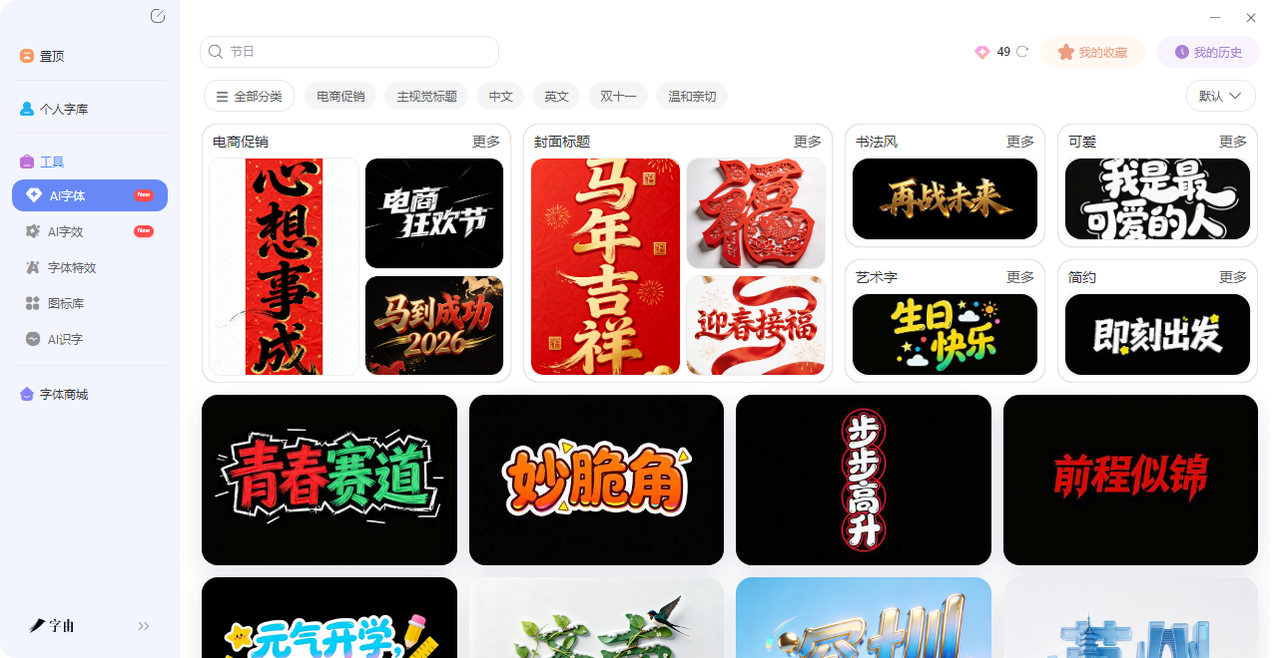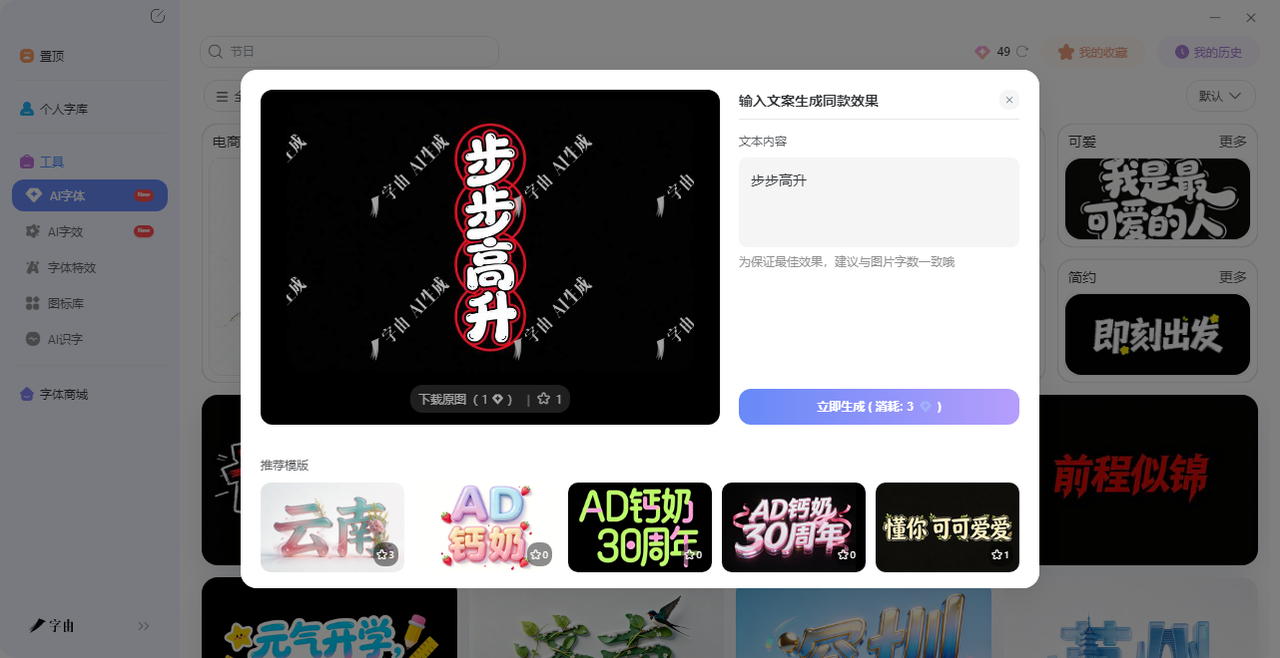
不会设计字体?这几个字体生成器一键搞定
每次刷到别人设计的海报,最让我眼馋的不是构图多精妙,而是那几个标题字——金属质感、霓虹闪烁、水彩晕染,怎么看怎么高级。自己也想要同样的效果。但是在发现捷径之前,我都是自己一板一眼地设计,但是困难重重并且效率非常低。后来我发现,这种“想要又做不出来”的尴尬,根本不是技术问题,而是没用对工具。今天要聊的字体生成器,就是专门解决这个问题的,今天介绍的这5个字体生成器绝对能帮到你,需要的快收藏吧!
字由的“AI字体”功能,本质上就是一个字体生成器。它把霓虹、金属、国潮、手写这些效果做成了模板,你只需要输入文字,选个顺眼的,点一下生成,就能拿到一张带特效的艺术字。不需要下载字体,不需要安装软件,甚至不需要打开PS——整个过程都在浏览器里完成,最后下载透明背景PNG,拖进设计软件就能用。
具体怎么使用呢,下面是简要的步骤:
- 第一步:在导航栏找到【字体工具】→【AI工具】→【AI字体】。
- 第二步:进入页面后,搜索框里输入你想要的效果,系统会筛出对应的模板。鼠标滑过模板,就能看到用你的文字实时展示的效果。这些模板不是那种千篇一律的预制货,而是真的考虑了不同设计场景。比如做电商促销,有“限时特惠”“满300减50”这种冲击力强的;做节日海报,有“元宵节快乐”“生日快乐”这种氛围感足的;做品牌Logo,有“CLASSY”这种高级简约的。每个模板点进去还能微调,颜色、背景、字间距都能改,不是那种“生成出来就定型”的死板工具。所以哪怕同一个模板,你改个颜色、换种排版,也能做出不一样的感觉。
- 第三步:选一个喜欢的,点击“做同款”,把模板里的文字换成你的标题(最好字数一致)。
- 第四步:点“立即生成”。等20-30秒,就能拿到一张高清艺术字图片。下载时可以选择透明背景,直接用在设计里。
步骤十分简单,哪怕你是0 基础的新手,也能够完全使用。而且字由的AI字体模板库非常丰富,按场景分好了类:电商促销、主视觉标题、节日、国潮、科技、手写……每个分类下都有几十种风格。如果你有自己常用的字体,也可以先用字由的字体库选好基础字体,再用“AI字效”功能给它加特效,同样是一键搞定。
生成的图片可以直接用在海报、封面、短视频里。透明背景的PNG拖进PS、Canva、剪映,不需要抠图,不需要调色,直接叠加就行。如果你用的是PS、AI、Figma这些软件,字由的客户端还能一键应用字体——选中文字图层,在字由点一下,文字实时切换,不用下载安装。
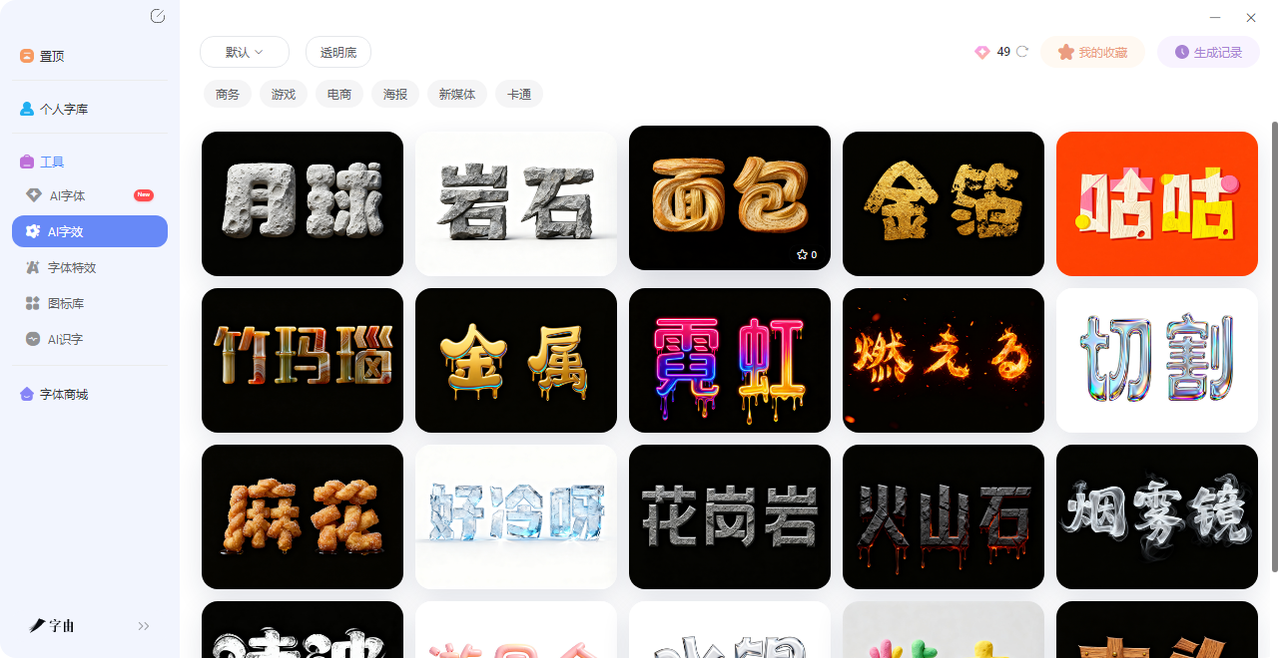
2、Font Generator
这个字体生成器和字由不一样,它不生成图片,而是把普通文字转换成各种花式字体,然后让你直接复制粘贴。适合用在社交媒体个人简介、评论区、游戏昵称等地方。打开网页,在输入框里打字,下面会立刻列出几十种不同风格的字体:粗体、斜体、手写体、哥特体、气泡体、上下颠倒体……点一下旁边的“Copy”按钮,就能复制到剪贴板,直接去微信、微博、抖音里粘贴。完全免费,无需注册。
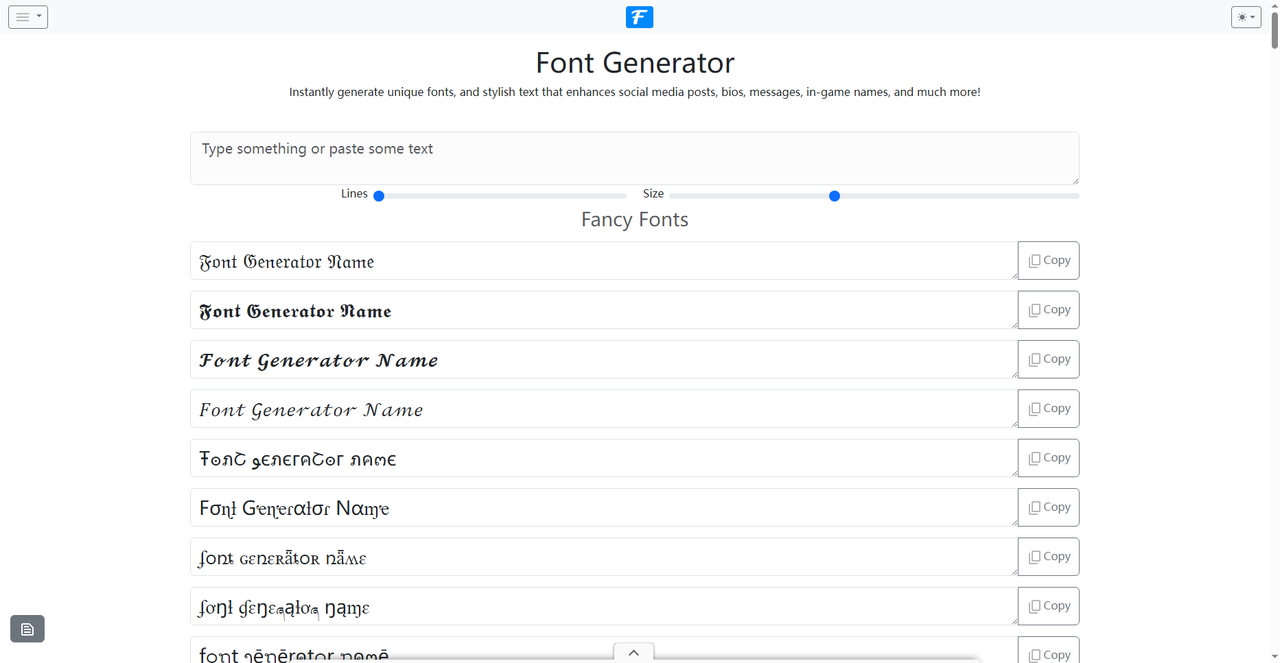
3、Fancy Text Generator
这个工具和上面那个类似,也是把普通文字转换成Unicode花式字体。但它的分类更细:下划线字体、草书字体、删除线字体、哥特字体、粗体、小字体、故障字体、气泡字体、上下颠倒字体、美学字体……总共加起来几十种。操作一样简单:输入文字,下方自动生成各种样式,点复制就行。适合喜欢在社交平台上“整活”的用户,发个带特殊字体的文案,回头率很高。
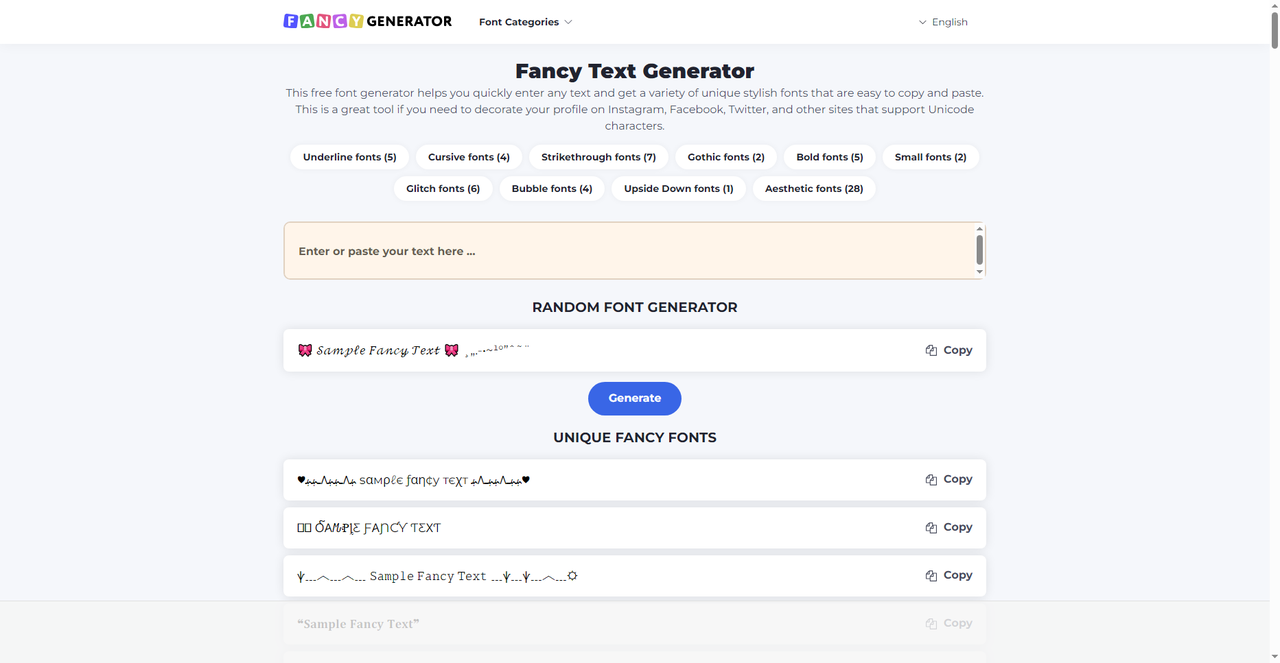
4、Fancy Text Generator
这个工具也是做文字转换的,但它多了一个功能:生成随机花式字体。点击“Generate”按钮,系统会随机给你几个不同风格的字体方案。适合懒得翻列表、只想碰运气的用户。它还附带了一个解释,告诉用户这些花式字体的原理——不是真的改变了字体,而是用了Unicode里的特殊字符。虽然技术原理讲得清楚,但普通用户只需要知道“怎么用”就够了。
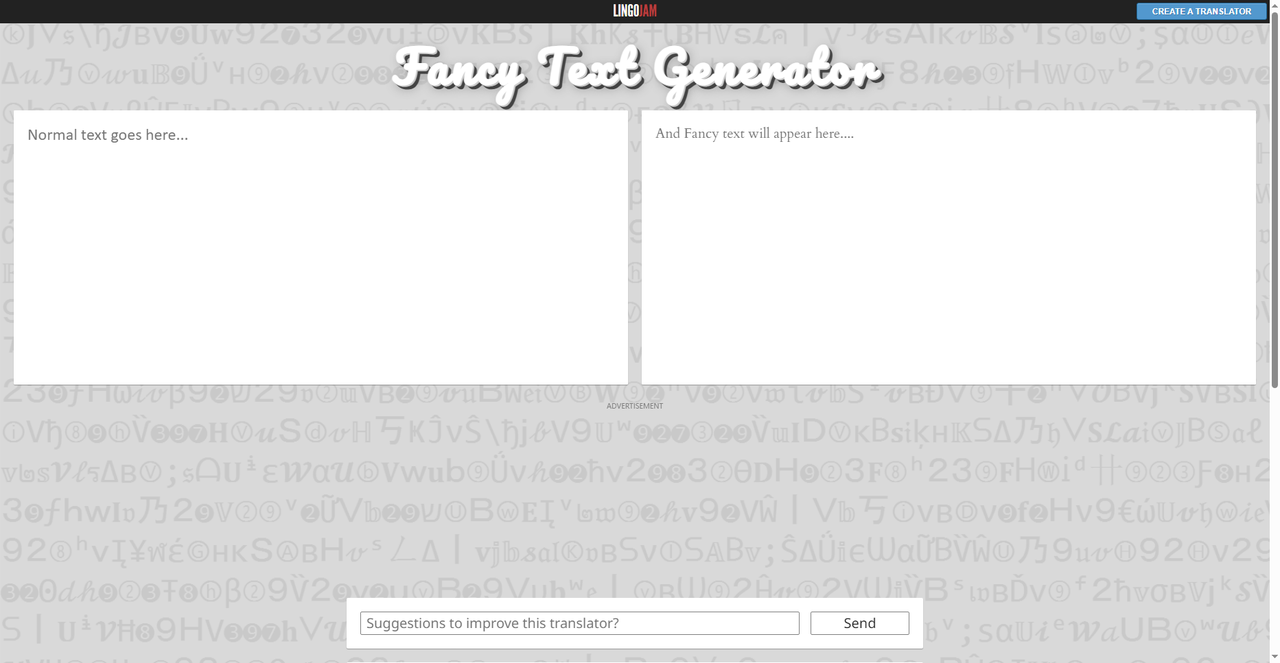
5、Musely
最后这个是一个中文的AI字体生成器,界面很简洁。输入文字,选择语言(支持中文),点击生成,AI就会输出带艺术效果的文字。从截图看,它还能调整一些高级设置,虽然具体参数没展示,但“AI”这个关键词说明它也是用模型来生成。不过这个工具需要过验证码,可能是防机器人的机制。生成效果如何,可以自己试试。如果你想要中文的艺术字效果的话,建议还是字由。
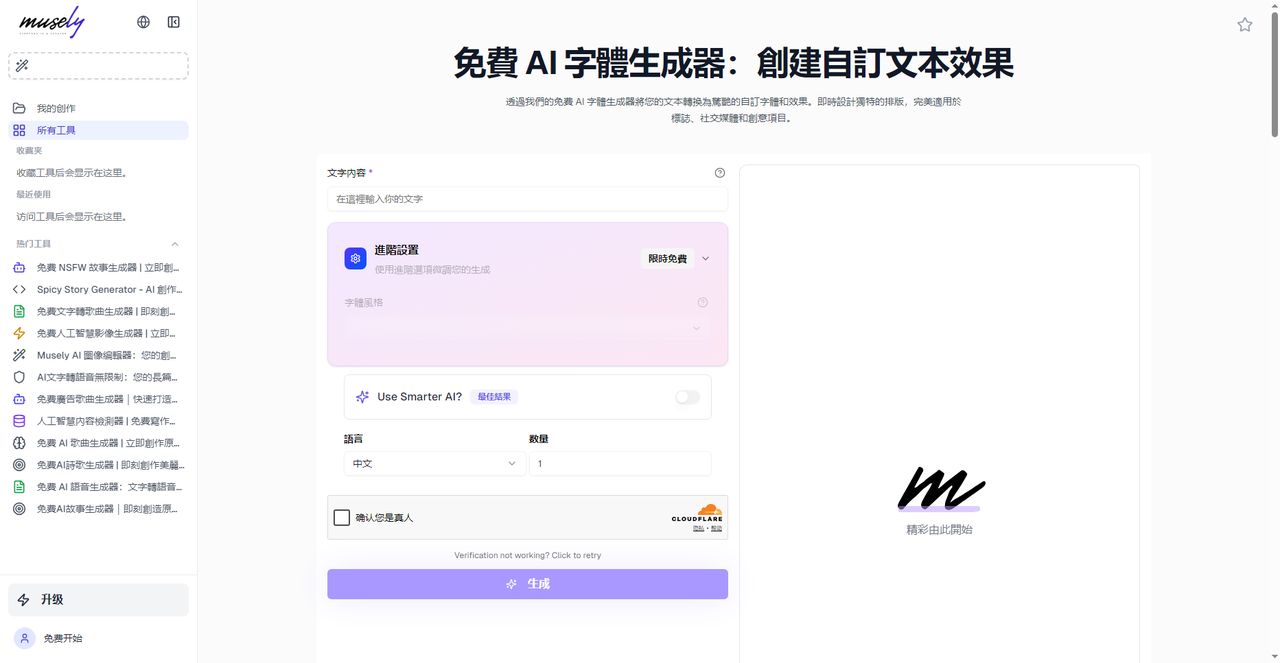
以前觉得设计字体是专业设计师的事,现在发现,用对工具,谁都能做出好看的标题字。这5 个字体生成器,有用来做社交媒体花式文案的,有用来生成图片艺术字的。而字由对我来说,是那个最实在的——打开网页,搜个“霓虹”,点个模板,填上文字,几十秒就能拿到一张能用的艺术字。它解决的不是“能不能做”,而是“能不能快”。如果你也经常被标题字卡住,不妨去试试,看能不能让灵感来得更顺畅些。